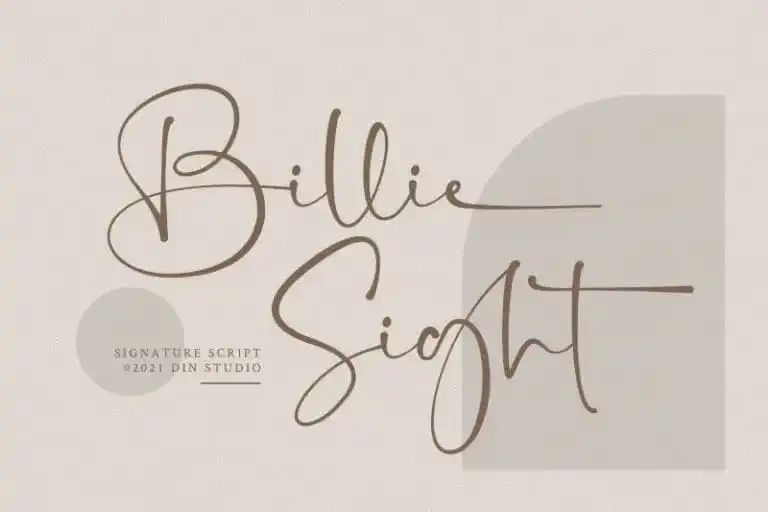
Billie Sight Calligraphy Font – Download Grátis
Billie Sight Calligraphy Font é uma elegante tipografia de grafite moderna criada por Din Studio para complementar seu público-alvo ou convidados. Com cada traço e curva meticulosamente projetado, a fonte captura o encanto do requinte e da sofisticação. É ideal para posts em redes sociais e anúncios, design de citações impressas, roupas com estampas, embalagens ou mesmo como fundo de texto moderno sobre qualquer imagem de fundo. Seja você uma marca ou um criador de conteúdo online, Billie Sight Calligraphy é a fonte perfeita para complementar seu estilo e torná-lo ainda mais único.